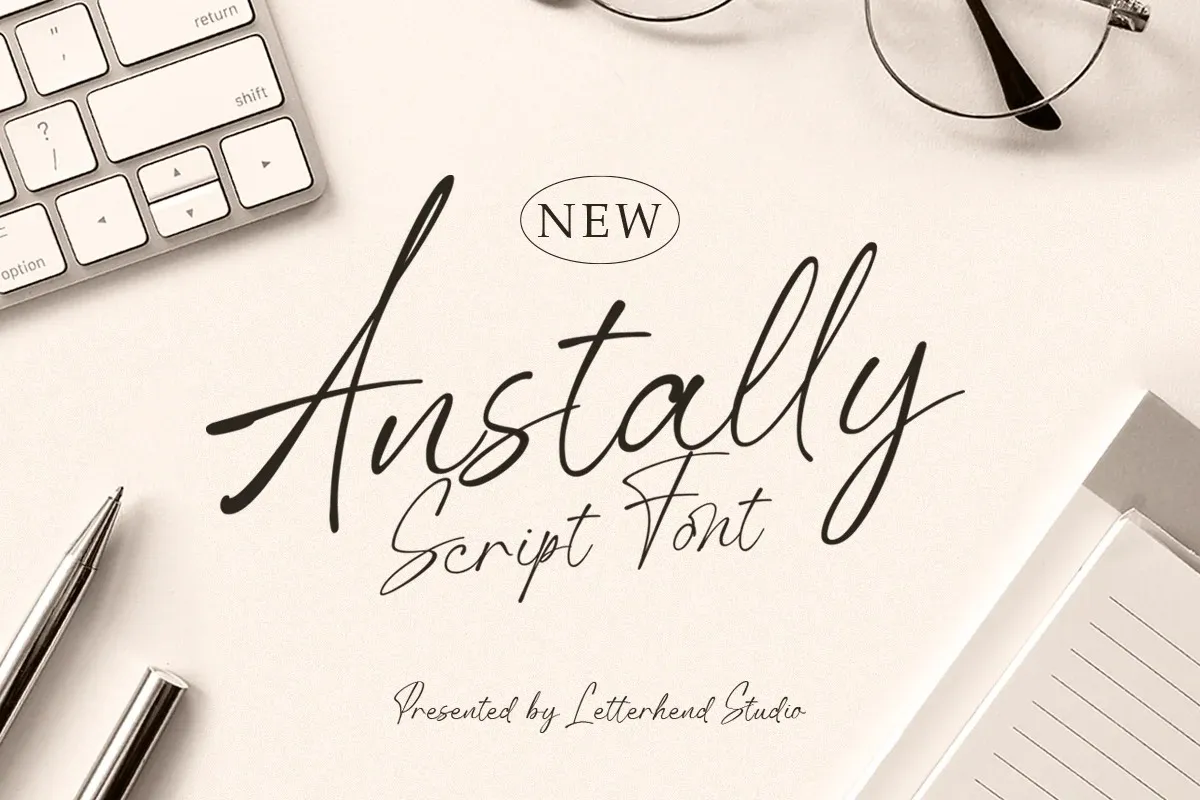
Anstally Font é uma fonte de script que oferece um toque natural e autêntico à qualquer projeto ao qual seja aplicada. Criada pelo estúdio Letterhend Studio, essa fonte foi projetada para ser perfeitamente adaptável a diversas formas formais como cartões de aniversário, embalagens, revistas, livros e até mesmo carteiras de roupas ou maquiagem. Seu toque autêntico é perfeito para aplicar em logotipos e outros formatos formais, garantindo um visual que combina com praticamente qualquer tipo de publicidade. O design de Anstally Font traz uma sensação agradável do estilo do papel manual à sua utilização, tornando-a uma opção ideal para aqueles buscando algo único e autêntico no seu próximo projeto gráfico.